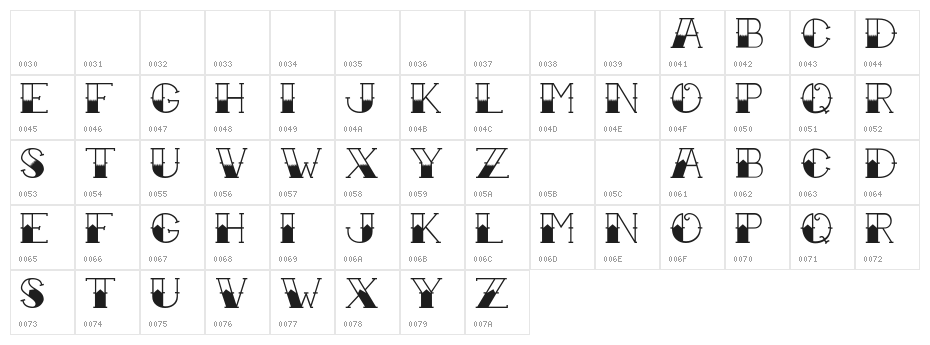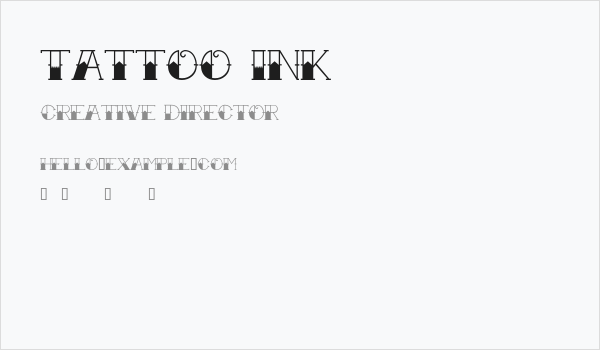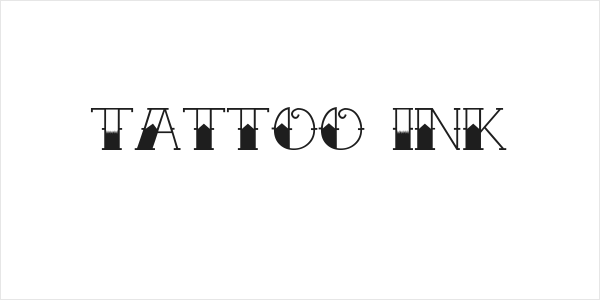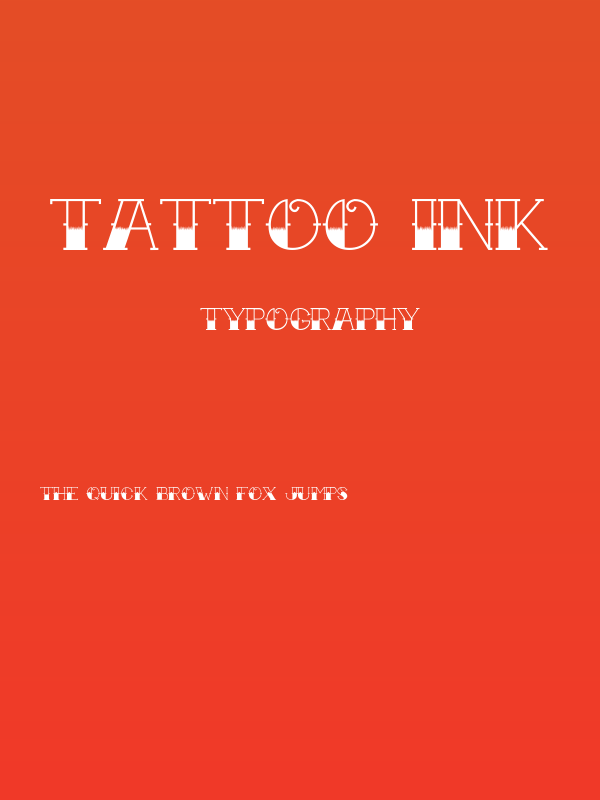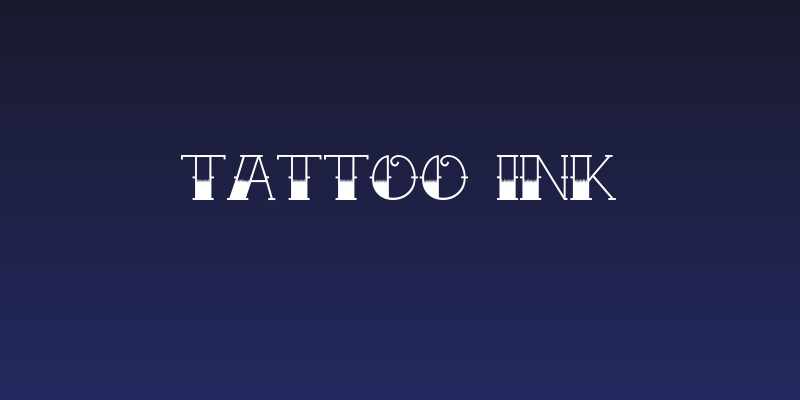
Tattoo Ink Font
| श्रेणियाँ | Outline |
| कंट्रास्ट | High |
| समग्र शैली | Modern, Industrial |
| उपयोग का मामला | Logos, Posters, Branding |
| सुझाए गए प्रोजेक्ट | Ideal for tattoo designs, urban-themed posters, branding for edgy products, or any project requiring a bold, artistic statement. |